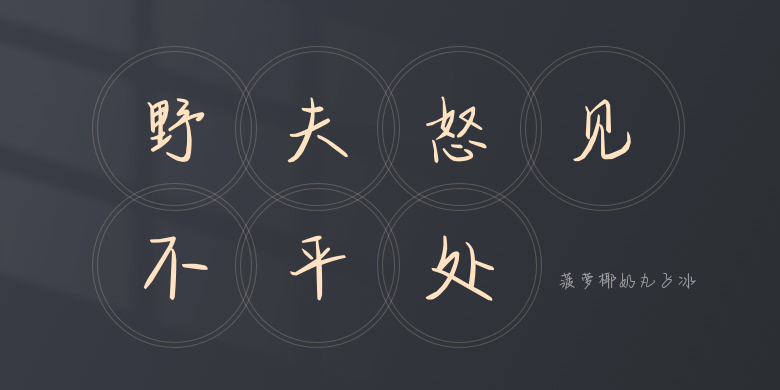
菠萝椰奶丸子冰
菠萝椰奶丸子冰,这款字体结构工整、笔画清晰,兼顾美观与易读性,适用于标题、正文、海报、包装、LOGO 等多种场景。字形优雅稳定,风格百搭耐看,适配日常排版与创意设计,让文字呈现更舒适、更具质感。菠萝椰奶丸子冰一笔一画,皆是细节,以均衡的比例、流畅的线条打造舒适视觉体验,字形端正大气,风格简约现代。无论是商业设计、品牌宣传还是日常排版,都能轻松驾驭,让文字更有格调与力量。菠萝椰奶丸子冰字体下载。